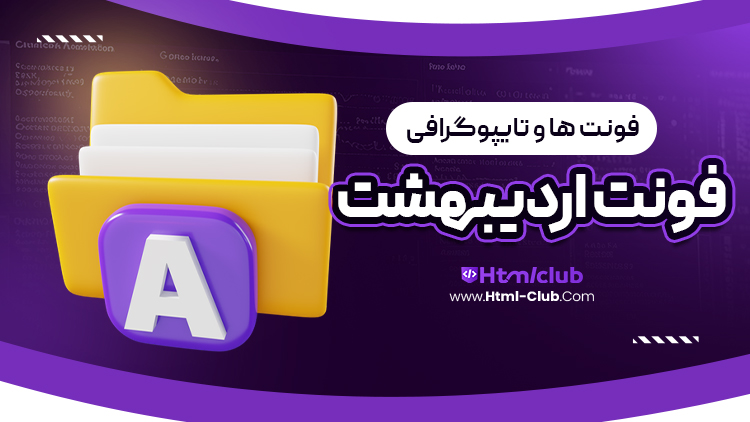
فونت اردیبهشت در سایت html club برای شما عزیزان قرار داده شده است.در دنیای پرسرعت و پرهیاهوی امروز، جایی که کلمات به سرعت رد و بدل می‌شوند، فونت اردیبهشت به عنوان یک نغمه آرامش‌بخش و دلنشین در میان دیگر فونت‌ها می‌درخشد. این فونت، همچون نسیم ملایم بهاری، با خطوط نرم و منحنی‌های دلپذیر خود، حس تازگی و زندگی را به متن‌ها می‌آورد.
ویژگی های برجسته فونت ابتکار:
نوآوری در طراحی
خطوط نرم و روان این فونت، یادآور شکوفه‌های بهاری است که در دل طبیعت می‌رویند. هر حرف به گونه‌ای طراحی شده که حس طبیعی و ارگانیک بودن را منتقل کند.پ
تنوع کاربرد
چه در طراحی وب‌سایت‌ها، چه در چاپ کتاب‌ها یا بروشورها، فونت اردیبهشت با زیبایی خاص خود، هر محیطی را زینت می‌بخشد و جذابیت بیشتری به محتوای شما اضافه می‌کند.
شخصیت منحصر به فرد
ونت اردیبهشت با ایجاد حس آرامش و راحتی، خواننده را در دنیای خود غرق می‌کند. این ویژگی آن را به گزینه‌ای ایده‌آل برای متون ادبی، شعرها و نوشته‌های احساسی تبدیل کرده است.
پشتیبانی از زبان های مختلف
از ویژگی های فونت اردیبهشت می توان به امکان تایپوگرافی و استفاده از حروف زینتی مثل ی کشیده ، تخصیص فرم های مختلف از یک حرف به گلیف های متعدد ، پشتیبانی از زبان های فارسی ، عربی و انگلیسی (که بدون تعویض قلم و زبان امکان تایپ انگلیسیبا قلم هم وزن قلم اصلی نیز فراهم می باشد) لیگچر ، بیش از صد ها کرنینک فشرده ، اسکریپت نویسی ، جانمایی اختصاصی موقعیت اعراب نسبت به هر حرف و نوشته ، امکان عبارات علیه السلام و صلی الله علیه و آله سلم و … اشاره نمود .
با استفاده از این فونت، شما می‌توانید داستان‌های خود را با ظرافت و لطافت بیشتری بیان کنید و خوانندگان خود را به دنیای خیال‌انگیزتان دعوت نمایید. در واقع، هر بار که از فونت اردیبهشت استفاده می‌کنید، به نوعی جشنواره‌ای از زیبایی و احساسات را آغاز می‌کنید.